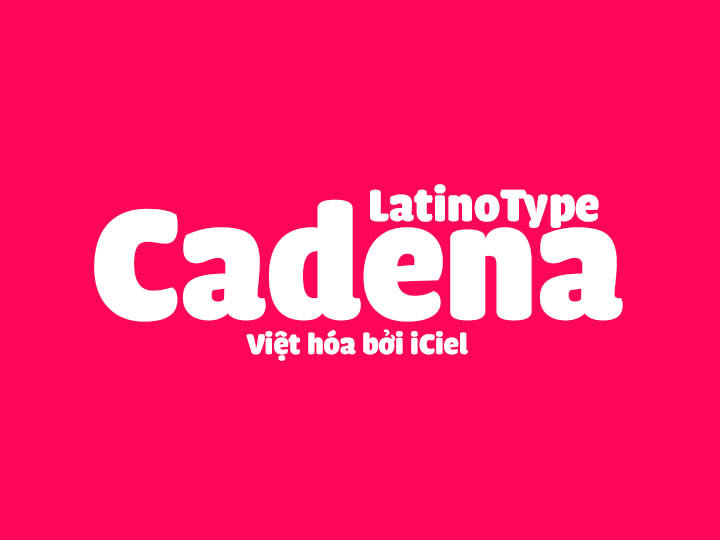
Font việt hóa iCiel Cadena
Trong thế giới thiết kế đồ họa hiện đại, việc lựa chọn một bộ Font Miễn Phí chất lượng là yếu tố quyết định sự thành công của một tác phẩm. Font việt hóa iCiel Cadena nổi lên như một lựa chọn hàng đầu cho những ai yêu thích phong cách thiết kế tròn trịa, hiện đại nhưng không kém phần thân thiện. Đây là bộ phông chữ được tinh chỉnh kỹ lưỡng, giúp người dùng Việt Nam dễ dàng tiếp cận mà không lo ngại về các lỗi hiển thị dấu câu thường gặp trong các phần mềm thiết kế chuyên dụng.
Ưu điểm nổi bật của Font việt hóa iCiel Cadena
Bộ font này sở hữu những đường nét hình học cân đối, tạo cảm giác vững chãi và chuyên nghiệp. Với cấu trúc các ký tự được bo tròn mềm mại, nó mang lại vẻ đẹp trẻ trung và năng động, rất phù hợp cho các bạn học sinh và giáo viên khi thiết kế slide bài giảng hoặc báo tường. Điểm đặc biệt là Font việt hóa iCiel Cadena hỗ trợ đầy đủ bộ gõ tiếng Việt, giúp văn bản luôn nhất quán và đẹp mắt trên mọi nền tảng.
Ứng dụng thực tiễn trong học tập và công việc
Nhờ tính đa dụng cao, bạn có thể sử dụng bộ phông này cho nhiều mục đích khác